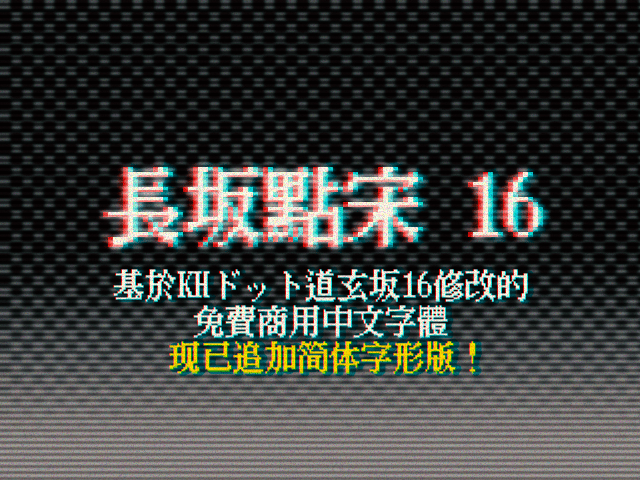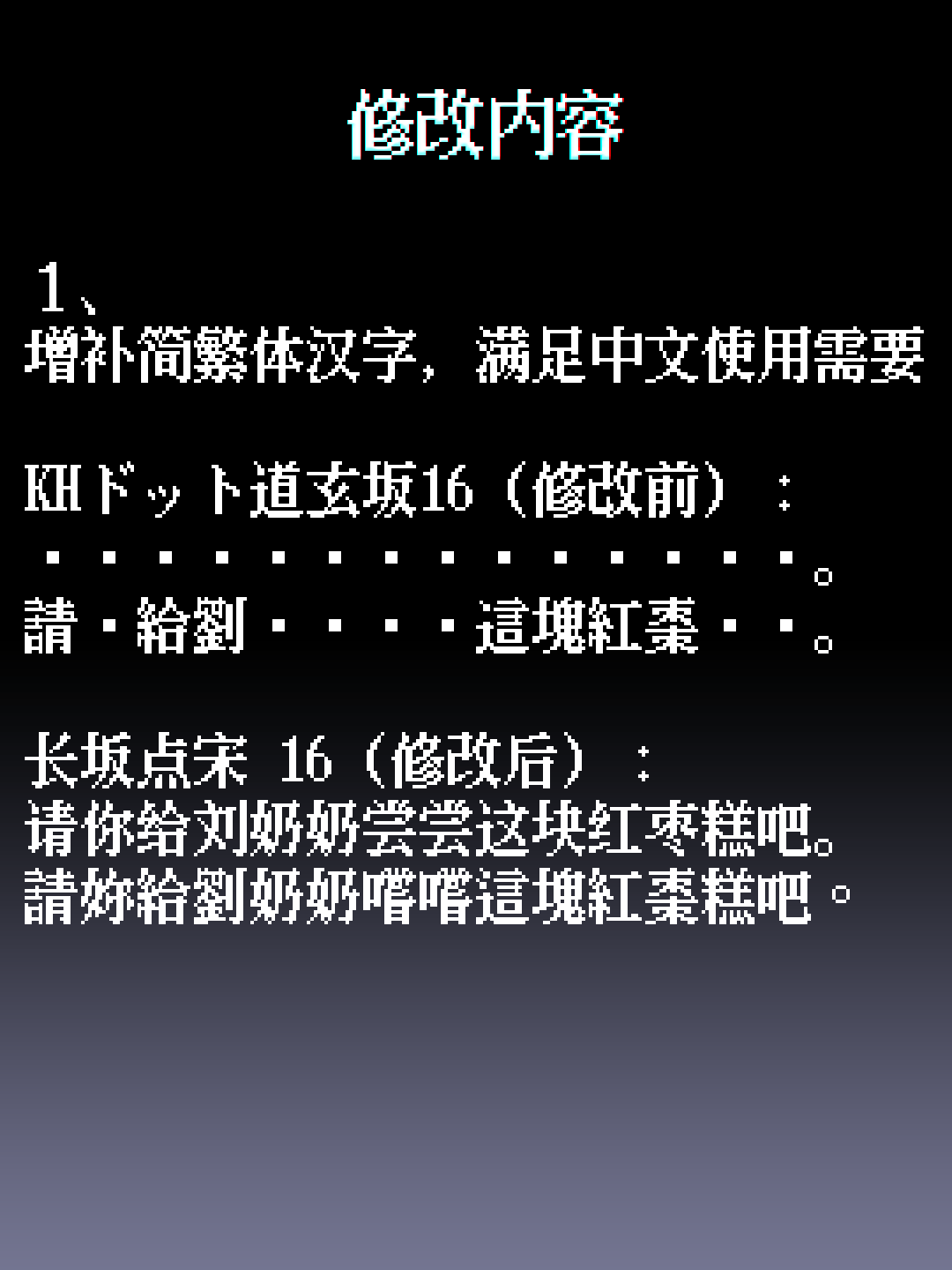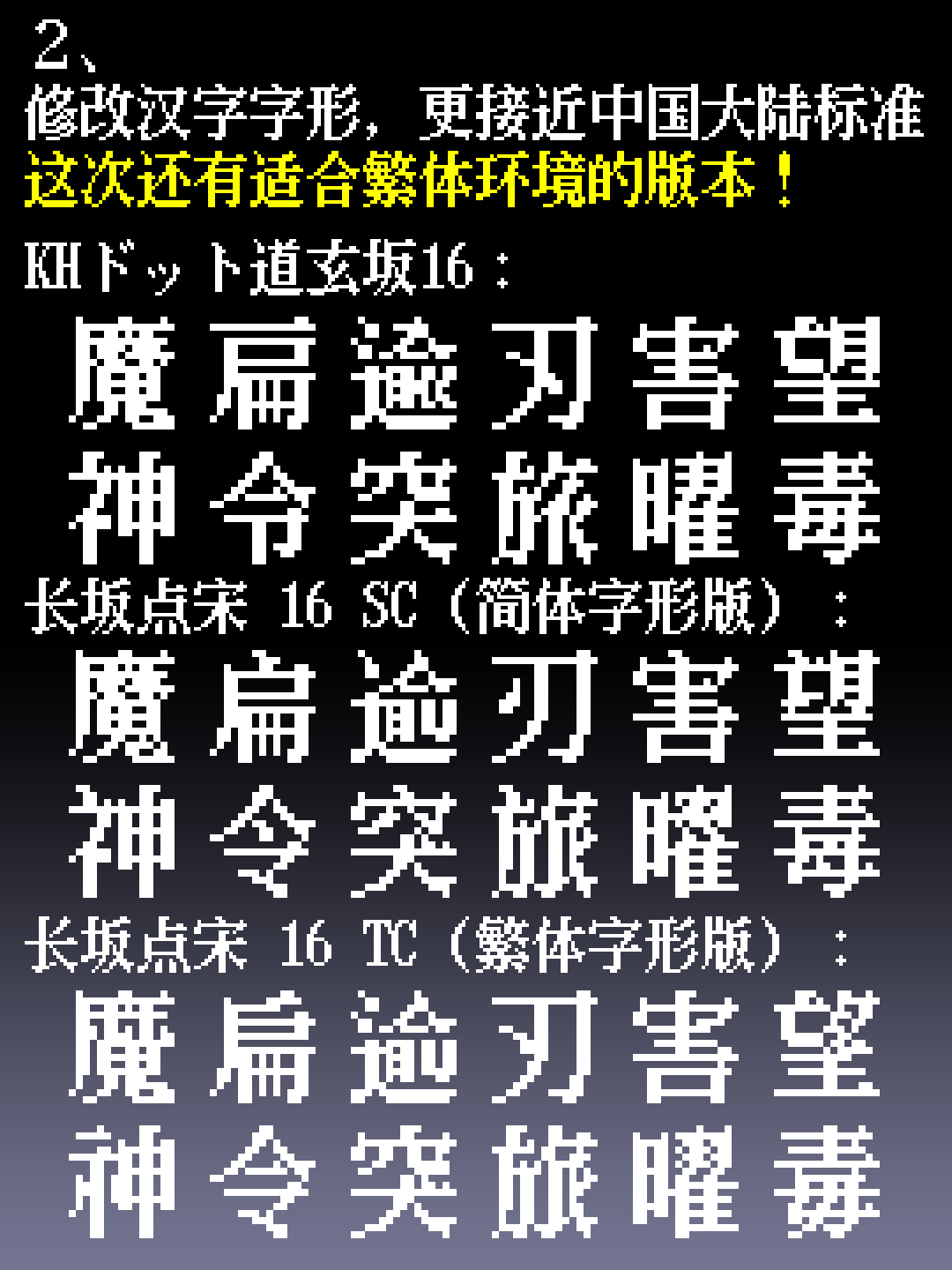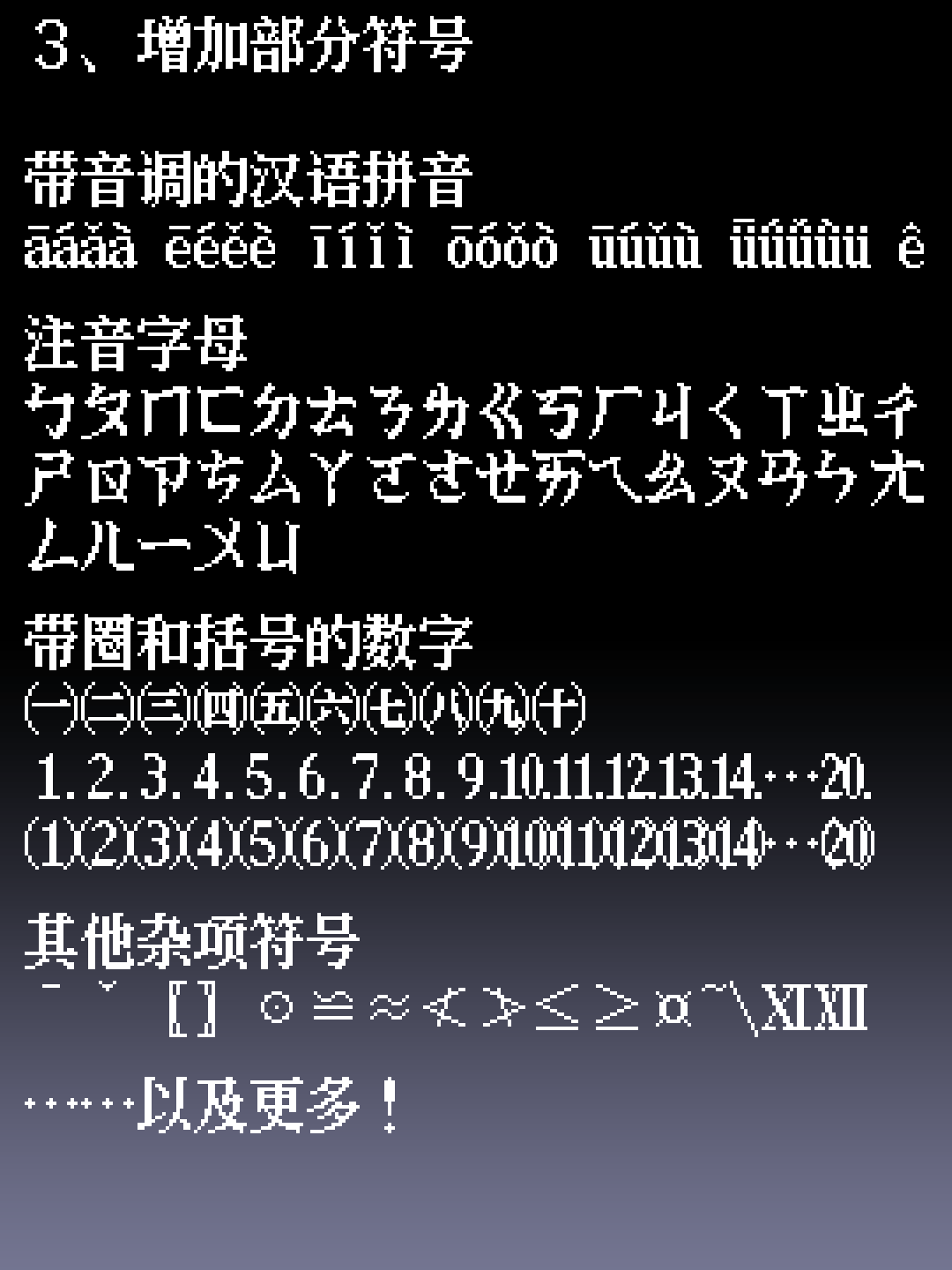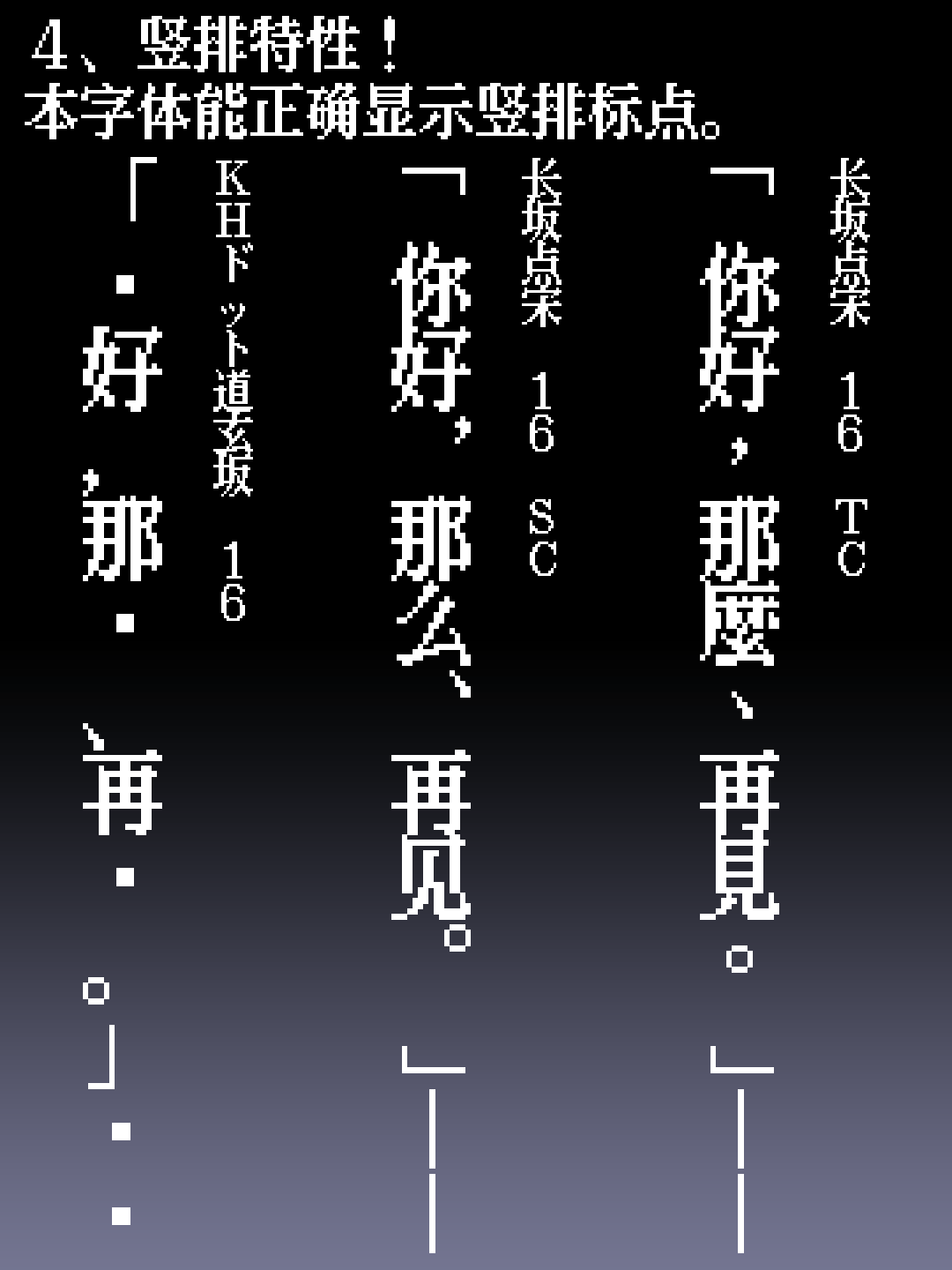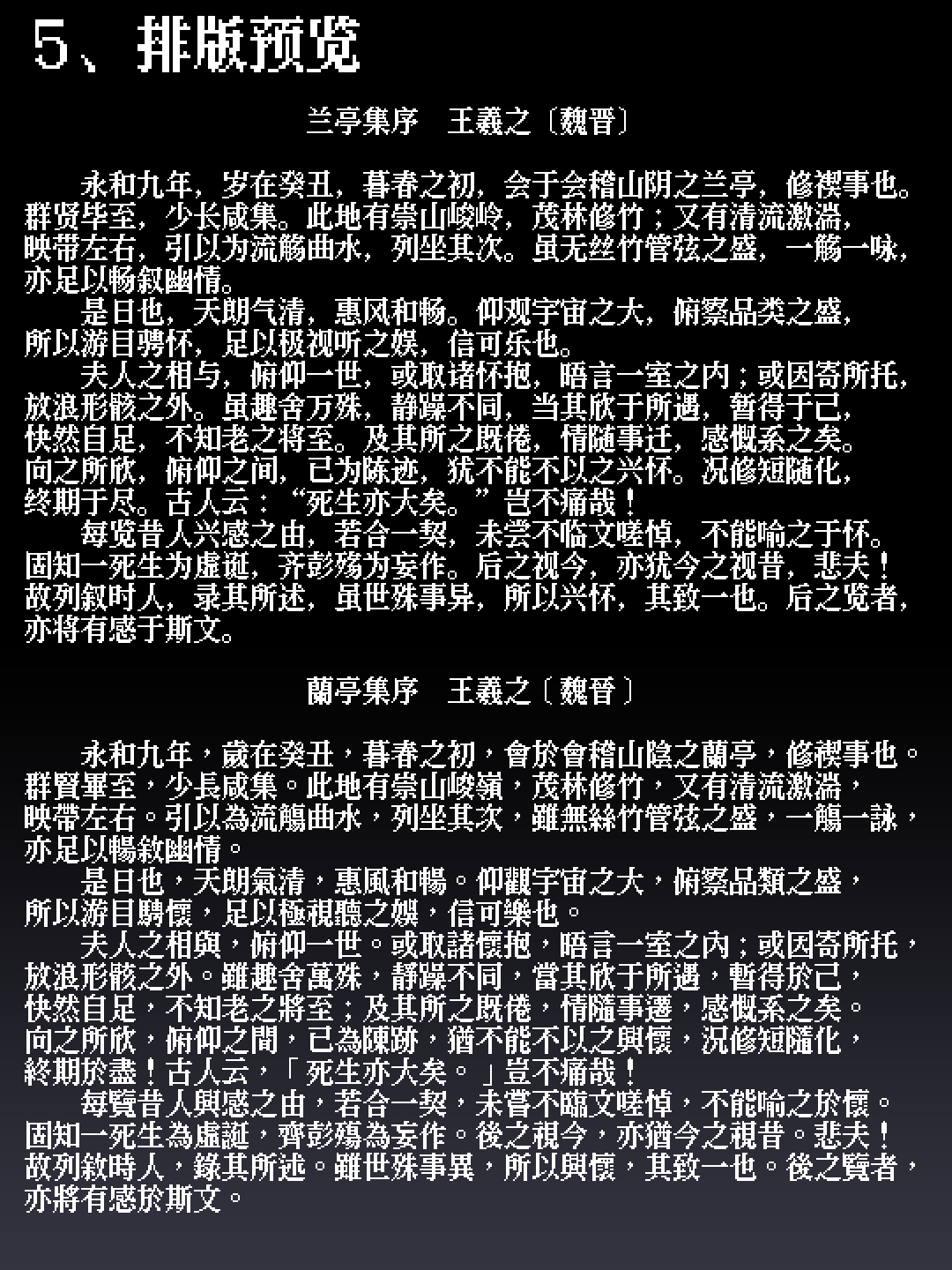
「长坂点宋 16」是在日本开源字体「KHドットフォントシリーズ」中的「KHドット道玄坂16」基础上,经过增补与适配,涵盖了更多简体与繁体汉字的一种16像素点阵粗宋体字型。其设计初衷是为了在需要复古像素风格的场景中提供清晰易读的显示效果,特别适用于怀旧风电子游戏、像素艺术作品以及具有年代感的街机招牌或菜单界面。由于采用了16像素的点阵网格与较粗的笔画风格,该字体在低分辨率环境下依然能保持良好的辨识度和视觉一致性。 与之前的「长坂点宋 12」版本(通常为单一字形集)不同,本项目为了更精确地服务不同地区的用字习惯,特地分为两个独立的版本发布:以“SC”为后缀的简体字形版,符合中国内地常用规范;以及以“TC”为后缀的繁体字形版,则适用于港台地区及需要繁体中文的场景。这种区分使得设计师在选择时能更贴合目标受众的实际用字需求,避免简繁混杂带来的视觉不统一问题。
基于KHドット道玄坂16修改的免费商用中文字体“長坂點宋 16”,现已追加简体字形版!
展示字体修改前后对比,包括增补简繁体汉字的效果示例,如“KH ドット道玄坂16”修改为“长坂点宋16”时文字从乱码变为正确显示的简体和繁体句子。
展示修改后更接近中国大陆标准的汉字字形样例,包含简体和繁体版本的字体示例,字体名称有 HH ドット道玄坂 16、长坂点宋 16 SC(简体字形版)和长坂点宋 16 TC(繁体字形版),样例包含“魔扁逾刃害望 神令突旅曜毒”等汉字。
增加的部分符号,包括带音调的汉语拼音字母、注音字母、带圈及括号的中文数字与阿拉伯数字、其他杂项符号等。
展示了该字体在日文、简体中文及繁体中文中竖排文字与标点的正确显示效果。
兰亭集序的排版预览,上方是简体中文,下方是繁体中文。
修复“芾”下部误作“市”的问题
修复“鵪”的避让问题
增加39个汉字。